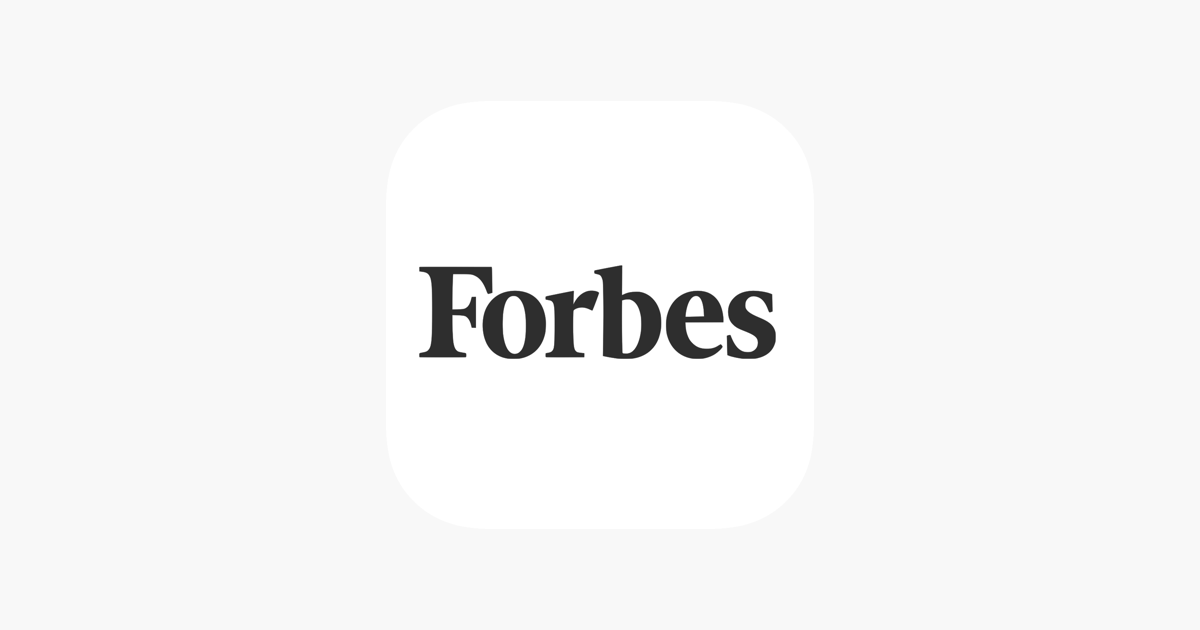
Клиент
Forbes – одно из наиболее авторитетных и известных финансово-экономических изданий в мире. Forbes Russia – российское представительство журнала.
Задача
Forbes Russia хотели увеличить число подписчиков электронной версии журнала и повысить его популярность среди мобильных пользователей. Для этого они решили изменить дизайн и подачу контента.
Электронную версию планировали реализовать на цифровой платформе Mag +. С ее помощью можно верстать журналы, используя привычные средства Adobe InDesign, а затем публиковать в App Store. Surf разработал дизайн-концепт для новой электронной версии издания.
Вызовы
- На каком бы экране пользователь не находился, он должен понимать, что читает Forbes.
- В новой мобильной версии должно быть одинаково удобно читать длинные статьи, авторские колонки и короткие новости.
Что получилось
Мы разработали для Forbes Russia концепт дизайна для iOS-приложения. Учли все возможности и ограничения технологии Mag+. Подготовили пакет рекомендаций по дизайну мобильной версии журнала:
- макеты основных материалов;
- гайды по сеткам и текстовому набору.
Мы предложили изданию лаконичный дизайн в его фирменных цветах, основной акцент сделали на подаче контента – верстке, шрифтах.
Как мы это сделали
Электронная версия издания включала 2 основных раздела:
- Журнал — интерактивная версия, созданная при помощи Mag+.
- Новости — экран, отображающий мобильную версию сайта forbes.ru. В журнале используются ссылки на новости с сайта. По клику у пользователя открывается встроенный браузер, отображающий новость на сайте. Новости в концепте разделили по категориям.
Пользователь может перейти в нужную категорию или «провалиться» в заинтересовавшую новость.
Главные принципы лаконичного дизайна
Удобно читать с любого устройства. Пристальное внимание при разработке дизайна уделили тому, чтобы журнал было комфортно читать с разных устройств – большого экрана iPad или с маленького iPhone.
Версию для смартфонов сделали максимально легкой и простой, чтобы на экране помещалось как можно больше полезного контента.
Текст, шрифты и верстка в центре внимания. Основа лаконичного дизайна – это грамотная работа с текстом, когда особое внимание уделяется шрифтам и верстке.
Фирменные цвета как основа узнаваемого стиля Forbes. Чтобы сохранить стиль журнала, при оформлении мы использовали фирменные цвета издания – черный и золотой.
Дополнительные элементы стиля. Чтобы добавить стилю электронной версии четкости и строгости, мы использовали гравюрную стилизацию, геральдические элементы и варианты газетной верстки.
Также мы предложили Forbes Russia несколько вариантов использования интерактивной инфографики.
Основные разделы журнала в новом дизайне
К каждому материалу разработали индивидуальную обложку, привлекающую к нему внимание.
Блоки материалов отделяются друг от друга обложкой раздела с содержанием. Каждый раздел выделяется цветом.
Это же логическое выделение цветом использовали в оглавлении журнала.
Для колонки главного редактора и авторских материалов создали лаконичные макеты с версткой, в которой много «воздуха» сочетается с не меньшим количеством полезного контента.
Forbes Логотип и символ, значение, история, PNG, бренд
Большинство из нас привыкли к тому, как слово «Forbes» выглядит на обложке журнала, поскольку оно не изменилось за пару десятилетий.
Однако до этого было много переделок. В некоторые периоды знаки различия менялись ежегодно. Журнал много экспериментировал со шрифтами и стилем.
Значение и история
Журнал Forbes основан осенью 1917. Перед началом следующего года журнал использовал логотип, в котором буквы были украшены множеством росчерков. На самом деле это было во многом связано с движением «Искусства и ремесла», которое было очень популярно в Соединенных Штатах в то время.
1917 – 1918
Логотип 1918 года немного напоминал плакаты Первой мировой войны – чем-то напоминал стиль Ренессанса и изящных искусств.
1918 – 1922
Самый первый логотип известного журнала был представлен в 1918 и имел причудливую нестандартную надпись «Журнал Forbes» на двух уровнях. Все заглавные буквы шильдика выполнены игривым, но стильным шрифтом, из них выходят вытянутые и изогнутые линии.
1922 – 1924
Логотип Forbes 1922 года был чем-то похож на оригинальный из-за росчерков.
Однако на этот раз они были не такими заметными.